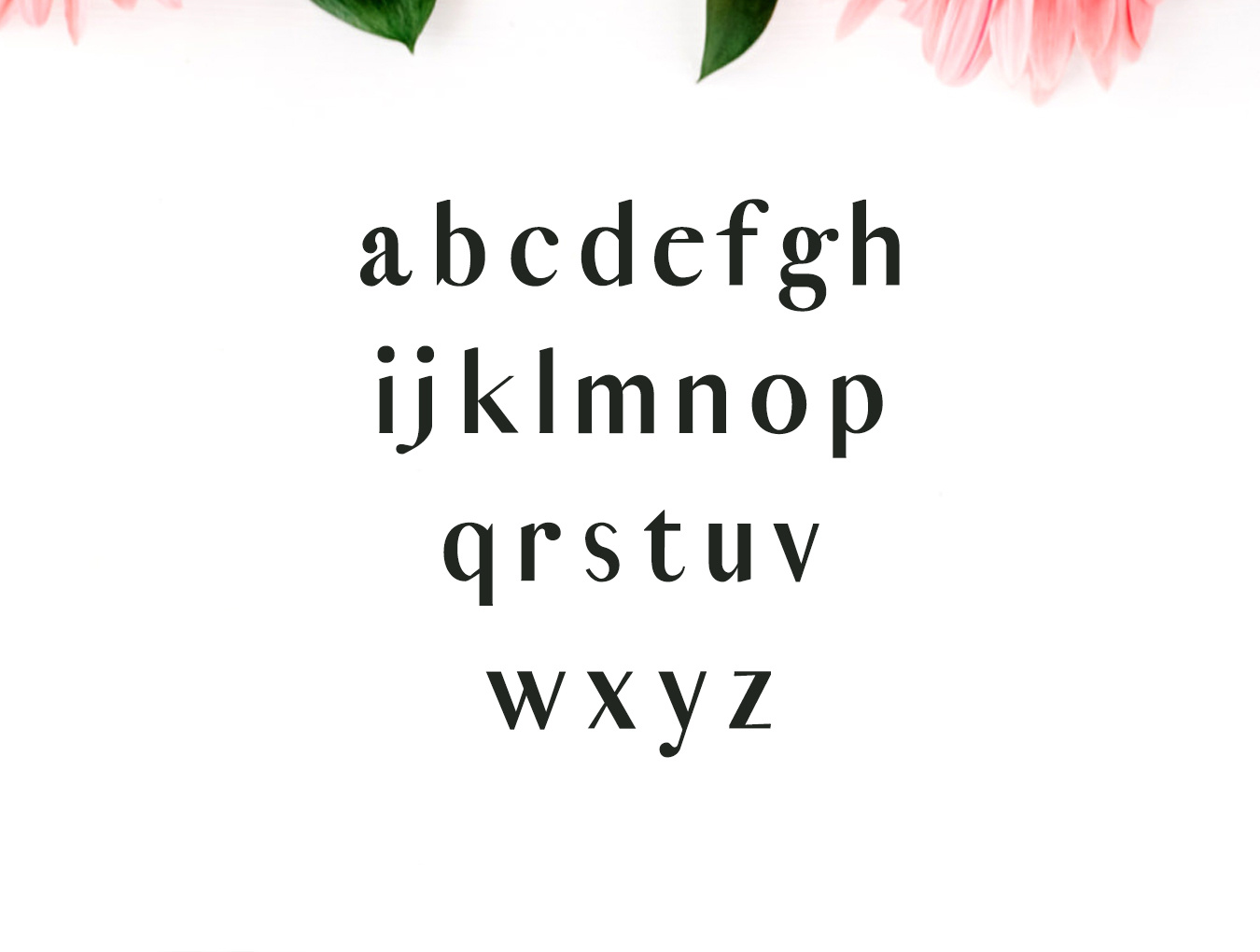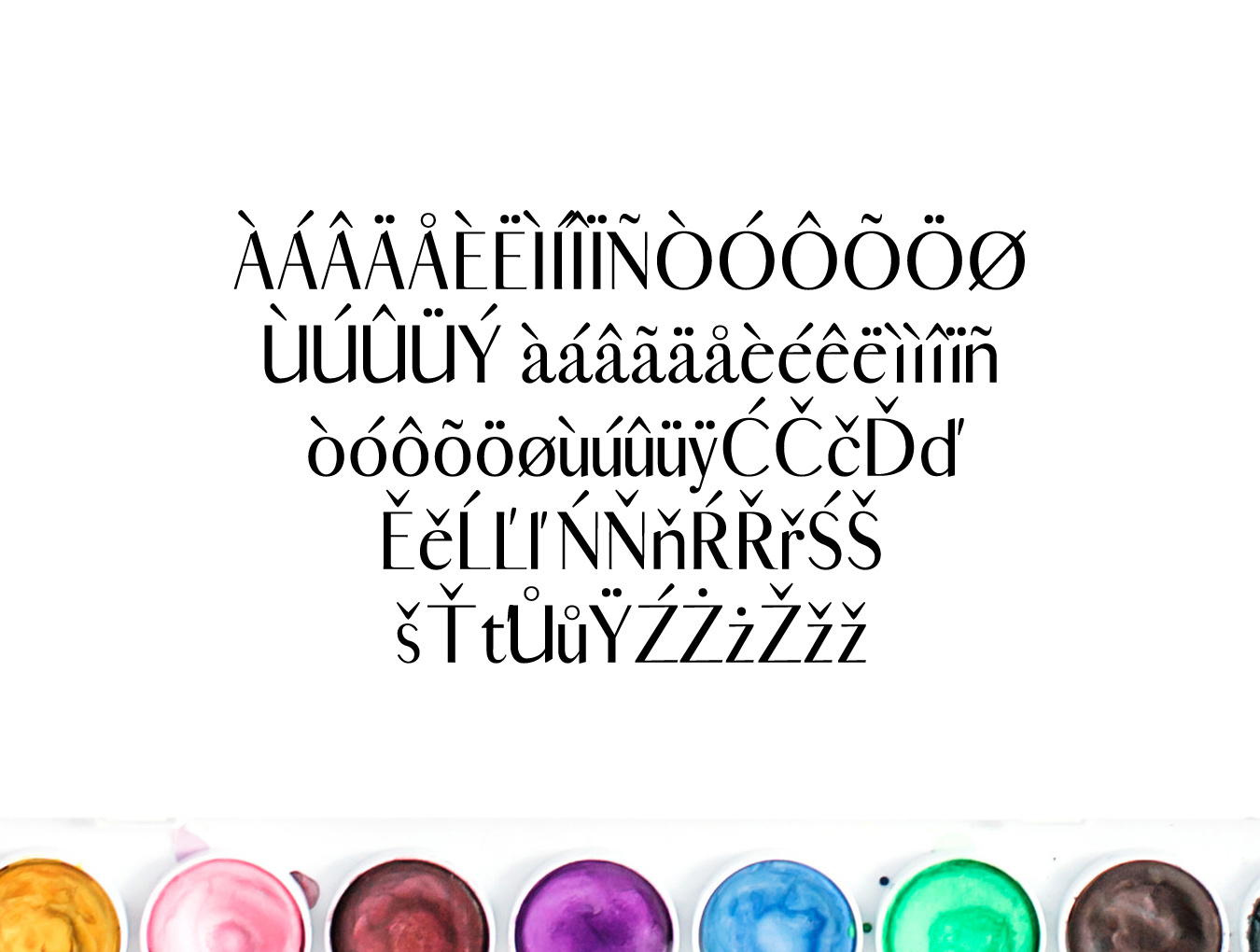
Cordaro Without Serif 2字体家庭装,Cordaro Sans Serif字体
Cordaro Sans Serif 2 Font Family Pack, Cordaro Sans Serif Typeface
Cordaro Sans Serif字体是一种最​​小的干净无衬线字体系列,包含2个砝码,它具有独特和现代的无衬线外观和感觉。非常适合华丽的徽标,标题,网页布局和品牌。如果你想尝试一个优雅的外观,它看起来华丽,所有帽子都有宽大的间距,或者在大写字母和小写字母中完美无瑕。